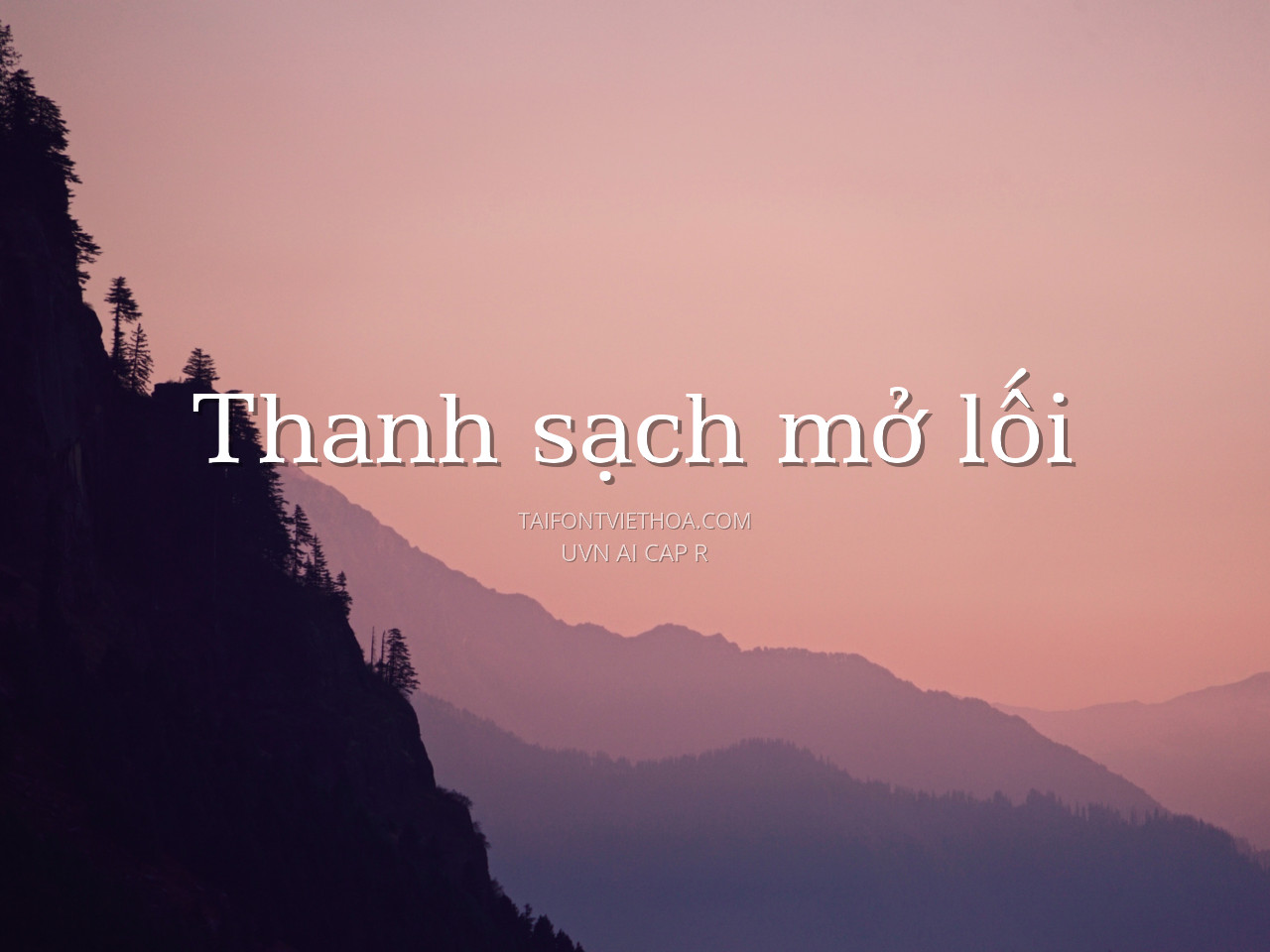
Font việt hóa UVN Ai Cap
Giới thiệu về font UVN Ai Cap
UVN Ai Cap là một bộ font mang đậm phong cách Ai Cập cổ đại (Egyptian style), được phát triển theo hướng slab serif đặc trưng với các nét thẳng và chân chữ dày, vuông vức. Đây là kiểu chữ thể hiện sức mạnh, sự vững chãi và cổ kính, thường xuất hiện trong các thiết kế mang chủ đề lịch sử, cổ đại hoặc cần tạo điểm nhấn độc đáo. Bộ font bao gồm nhiều trọng lượng như nhẹ (Nhe), đậm (Nang) và Regular, giúp người dùng linh hoạt hơn trong việc phối hợp kiểu chữ theo mục đích trình bày. Font này chỉ được sưu tầm và đăng bởi thành viên của Font Chuẩn và đã được taifontviethoa.com lựa chọn, kiểm nghiệm thực tế trong nhiều dự án thiết kế cổ trang, truyền thông nghệ thuật và giáo dục văn hóa.
Đặc điểm thiết kế và ứng dụng của UVN Ai Cap
UVN Ai Cap sở hữu các đường nét mạnh mẽ, chắc chắn với thân chữ dày dặn, dễ nhận diện. Các chữ cái có hình khối rõ ràng và phần chân chữ vuông tạo cảm giác cổ điển, trang nghiêm nhưng vẫn nổi bật khi hiển thị trên cả nền sáng và tối. Thiết kế này giúp font phát huy hiệu quả trong các dự án đòi hỏi sự uy nghi và bản sắc riêng biệt.
Font UVN Ai Cap thích hợp sử dụng cho tiêu đề sách lịch sử, poster phim cổ trang, bìa giáo trình, thiết kế bảo tàng, thương hiệu thủ công mỹ nghệ, bảng hiệu phong cách Đông phương và các dự án cần nhấn mạnh chiều sâu văn hóa. Ngành nghề ứng dụng: giáo dục, văn hóa – lịch sử, mỹ thuật, du lịch, thủ công truyền thống và xuất bản.